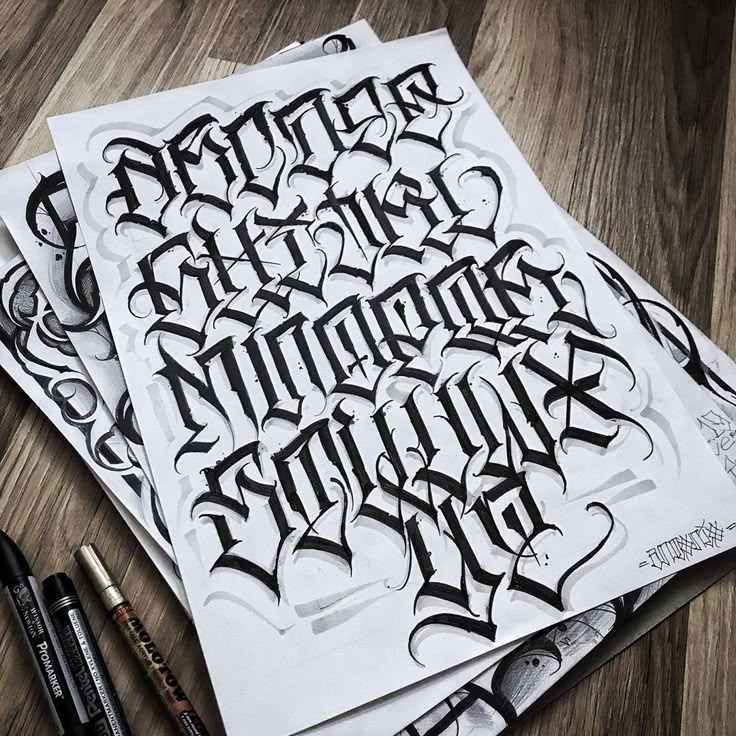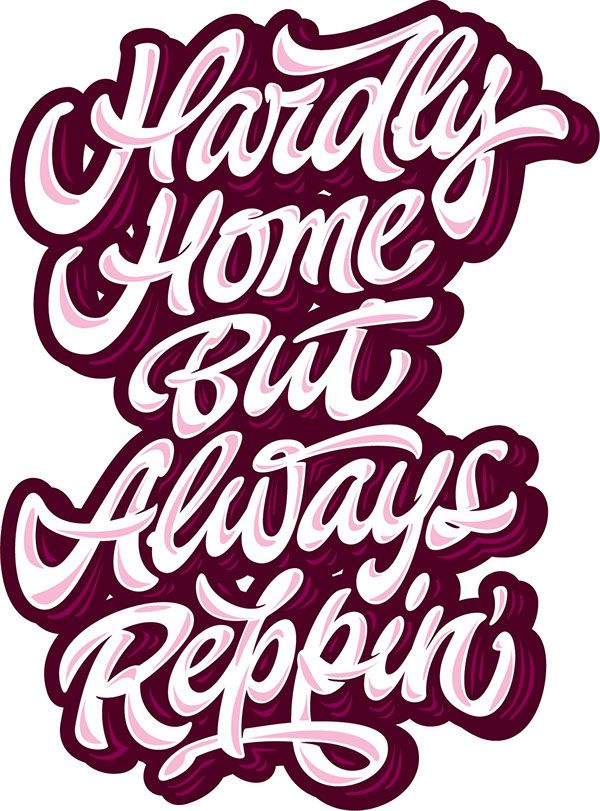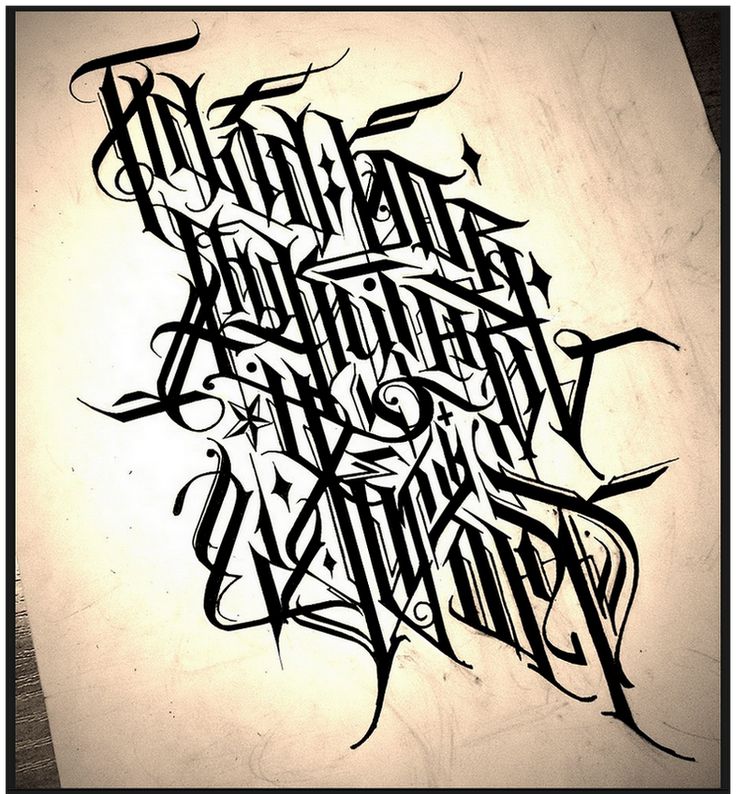
Винтажный леттеринг
Леттеринг сейчас очень популярен. По сути это шрифтовая иллюстрация, с помощью которой можно передать информацию текстом и сделать это красиво. Для знакомства с этим предметом мы создали специальный курс по самой вкусной дисциплине в этой области: винтажный леттеринг.
Кучерявые шрифты и виньетки, этикетки для сигар и фотосалонов, вывески дикого запада и прочие образцы типографики 19 века сегодня снова актуальны. Курс даст вам, с одной стороны, нужные навыки для создания хороших композиций, с другой — знания, которые помогут вам развиваться дальше, если шрифты увлекут вас по полной программе.
Леттеринг используется очень широко. Мы можем увидеть его на обложках книг, упаковках, афишах, объявлениях. Конечно, в логотипах. Меловой леттеринг — на вывесках кафе и ресторанов. А, если вы не собираетесь этим зарабатывать, можете просто поднять себе настроение, написав что-нибудь, что вас беспокоит или радует. Или делать отличные открытки друзьям и близким.
Чему вы научитесь
В рамках курса вы получите универсальные знания по композиции и шрифтам в целом, а так же изучим несколько базовых групп шрифтов и орнаментов, на основе которых можно делать уже самостоятельные работы.
1. Что такое леттеринг? Что такое шрифт и почему он такой?
Немного занудства и вместе с тем первые пробы.
Мы сразу займемся каллиграфией и постараемся понять, почему буквы выглядят так, как они выглядят.
Урок 2. Антиква, гротеск.
На этом занятии вы получите первые шестерёнки для сборки одной простой композиции.
Урок 3. Рукописный шрифт, акцидент.
Изучение и применение самого «красивого» шрифта.
Урок 4. Наполнение шрифта.
Придание шрифту формы, объёма, характера.
Урок 5 Декорация композиции.
То, что объединяет, украшает и заполняет шрифтовую иллюстрацию. Виньетки перестанут вас пугать и путать
Урок 6. Композиция.
Объединение всего пройденного материала единой целью: создать гармоничную цельную работу, все части которой подчинены общей идее.
Урок 7 Итоговая работа, наброски.
Теперь на основе всего, что было изучено, вы создадите собственную сложную шрифтовую иллюстрацию
Урок 8. Итоговая работа, выпускной
Мы доработаем вашу картинку, полюбуемся всем, что мы успели сделать и обменяемся впечатлениями.
В прошлой статье мы говорили о том, как разные шрифты отличаются друг от друга по своему рисунку и как эти отличия отражаются на их характере и удобочитаемости. Сегодня затронем другие аспекты, связанные с буквами, которые могут влиять на выбор шрифта для бренда.
Каллиграфия, леттеринг, шрифт
Все, конечно, что-то слышали о каллиграфии. Наверняка ещё в детстве встречали словосочетание «каллиграфический почерк», что на бытовом уровне значило просто «красивый почерк».
Русское рукописное письмо или попросту школьные прописи.
На самом деле почерк и каллиграфия — немного разные вещи. Почерк — просто характерные для любого пишущего детали его рукописного письма. А каллиграфию современное определение относит к искусству (очень древнему).
Кроме каллиграфии есть ещё леттеринг. Если упрощать, то они отличаются между собой тем, что каллиграфия пишется за один подход, минимальными движениями инструмента, а формы знаков леттеринга могут тем или иным способом многократно правиться и вообще чаще скорее рисуются, чем пишутся.
Чем же тогда шрифт отличается от леттеринга? Дело в том, что набором знаков шрифта можно пользоваться бесконечно, в том числе набирая тексты на клавиатуре, и все повторяемые символы будут идентичны. В то время как леттеринг — штучная работа.
С помощью копирования знаков из леттеринга можно сделать шрифт, но тогда он и перестанет быть леттерингом. Любопытно, что при всём этом, как мы писали в первой части, многие из шрифтов в своей графике опираются на каллиграфическую основу написания букв.
В брендинге леттеринг часто применяется, если речь заходит о логотипах, где уникальные буквы иногда помогают создать особенный образ. В то же время, в логотипах с использованием шрифтов в качестве основы нет ничего плохого, если это решение соответствует задаче, а айдентика состоит не только из логотипа.